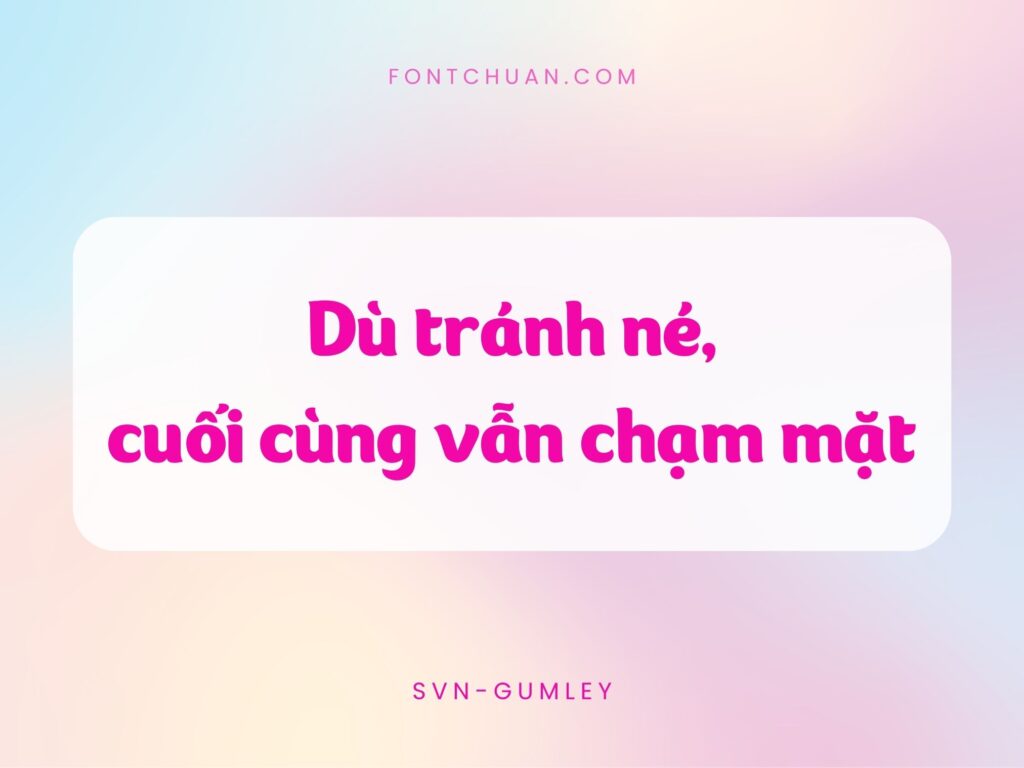
Font SVN Gumley Việt Hóa
Tác giả Font: Robert Corseanschi
Font SVN-Gumley là phiên bản Việt hóa của kiểu chữ Gumley, được thực hiện bởi Styleno.1 Fonts. Gumley là một phông chữ mang lại cảm giác tự nhiên, tươi mới, lấy cảm hứng từ thiên nhiên, đồng thời có sự mềm mại, phù hợp cho các thiết kế cần sự thân thiện và gần gũi.
SVN-Gumley lý tưởng cho các dự án thiết kế yêu cầu sự tự nhiên và sáng tạo, như thiết kế logo, tiêu đề, bao bì sản phẩm và các ấn phẩm quảng cáo. Các ngành nghề như quảng cáo, ẩm thực và spa có thể tận dụng phông chữ này để tạo điểm nhấn trong thiết kế. Ngoài ra, phông chữ cũng thích hợp cho các sự kiện như Tết, Giáng sinh, Valentine và các lễ hội khác.